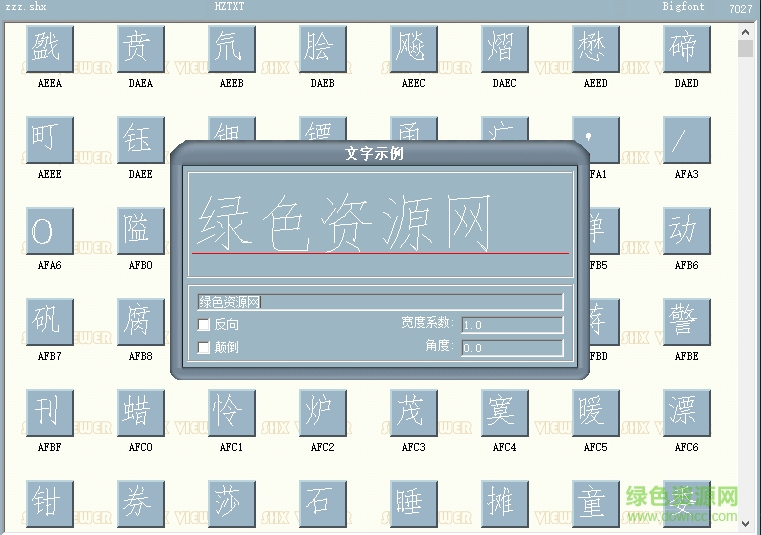
zzz.shx是一款autocad專用字體。用戶若不安裝這款字體文件,將無法打開使用這款字體的cad文件。歡迎需要的用戶來下載這款cad字體。
AutoCAD和一些兼容CAD專用的字體。
采用矢量的方式定義的字體,字體由線條構(gòu)成,不填充。
相應(yīng)的字庫文件分三類:
小字體:只包含英文、數(shù)字和一些符號(hào),總共只有256個(gè)字。
大字體:可容納65535個(gè)文字,一般用于定義中、日、韓等亞洲文字。
符號(hào)形:定義一些公差標(biāo)注、線型等使用的圖形(SHAPE)。